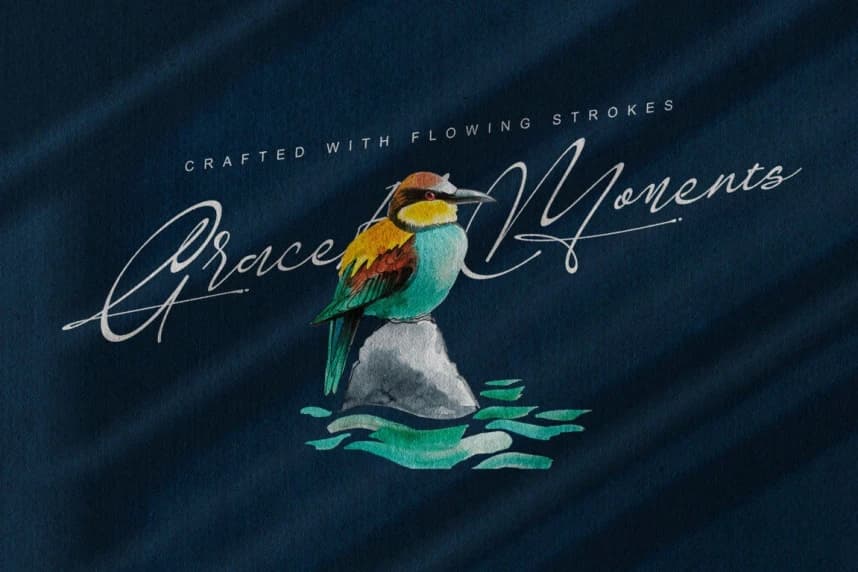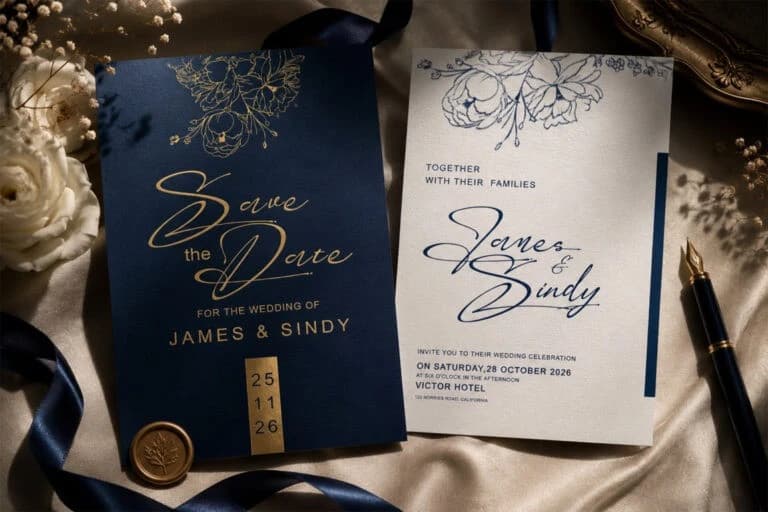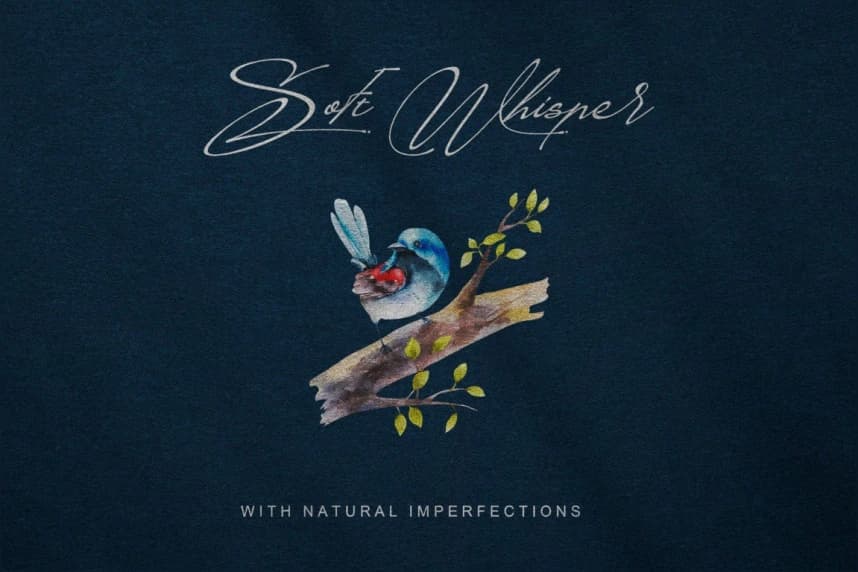
Maisonelle Yazı Tipi
Maisonelle Font, akıcı çizgiler, zarif eğriler ve doğal kusurlarla otantik imza yazımının güzelliğini yakalamak için tasarlanmış zarif bir el yazısı fontudur. Şık karakteri kişisel ve sofistike bir dokunuş katar.
Maisonelle Font, akıcı çizgiler, zarif eğriler ve doğal kusurlarla otantik imza yazımının güzelliğini yakalamak üzere tasarlanmış zarif bir el yazısı fontudur. Zarif karakteri kişisel ve sofistike bir dokunuş sunar